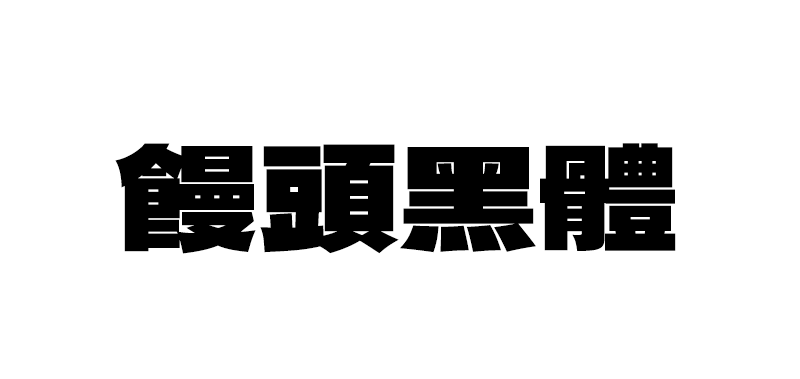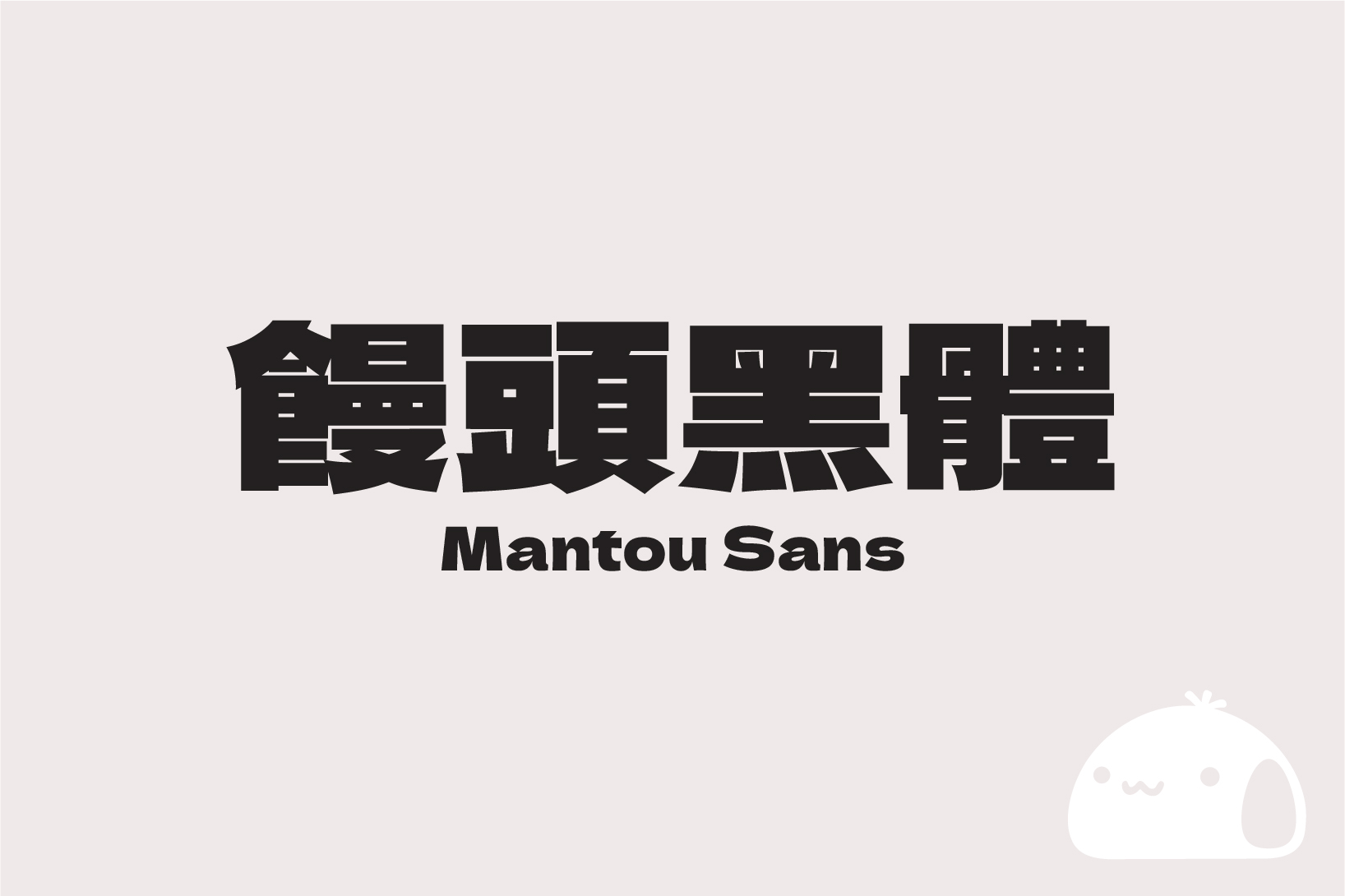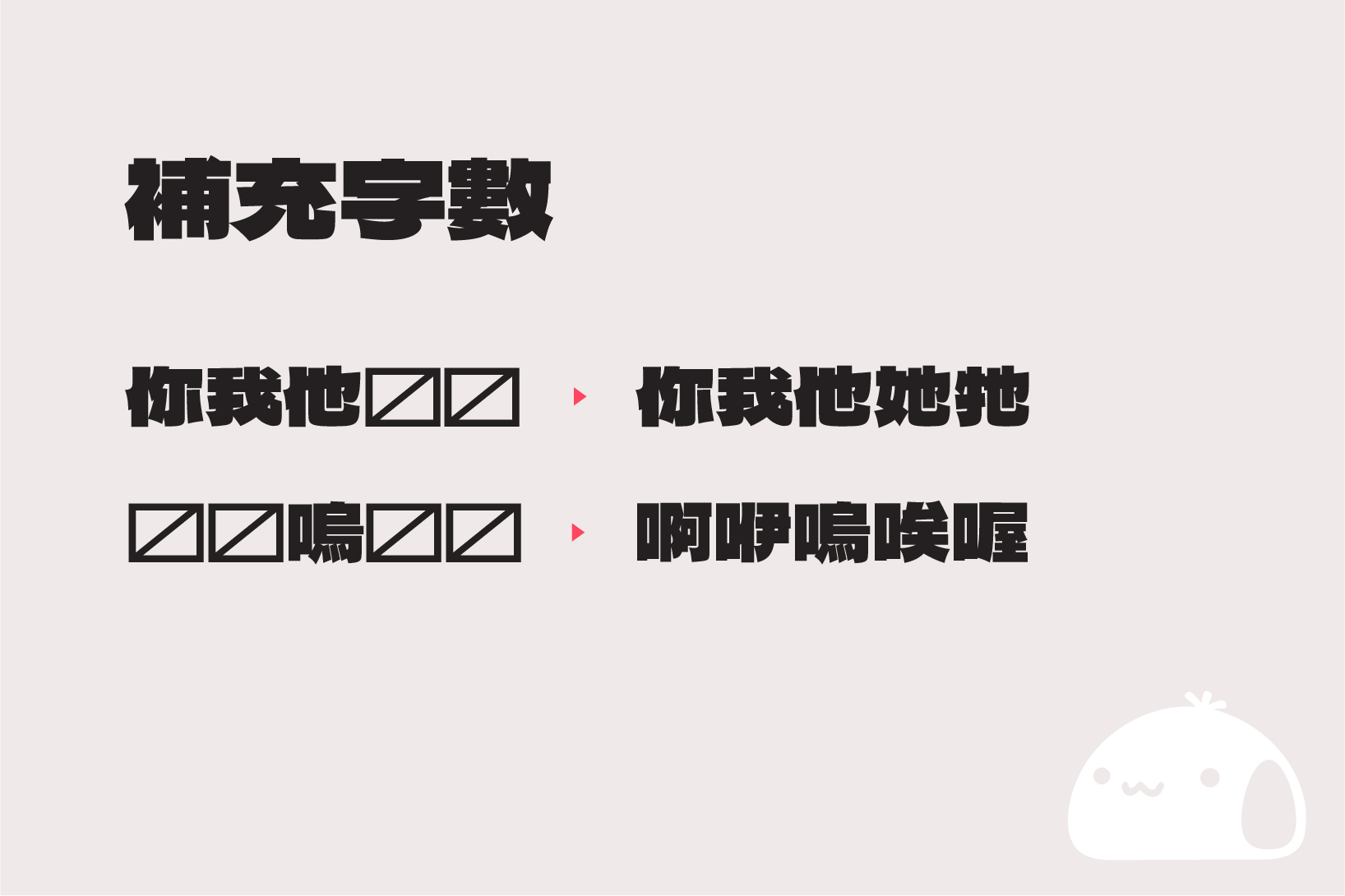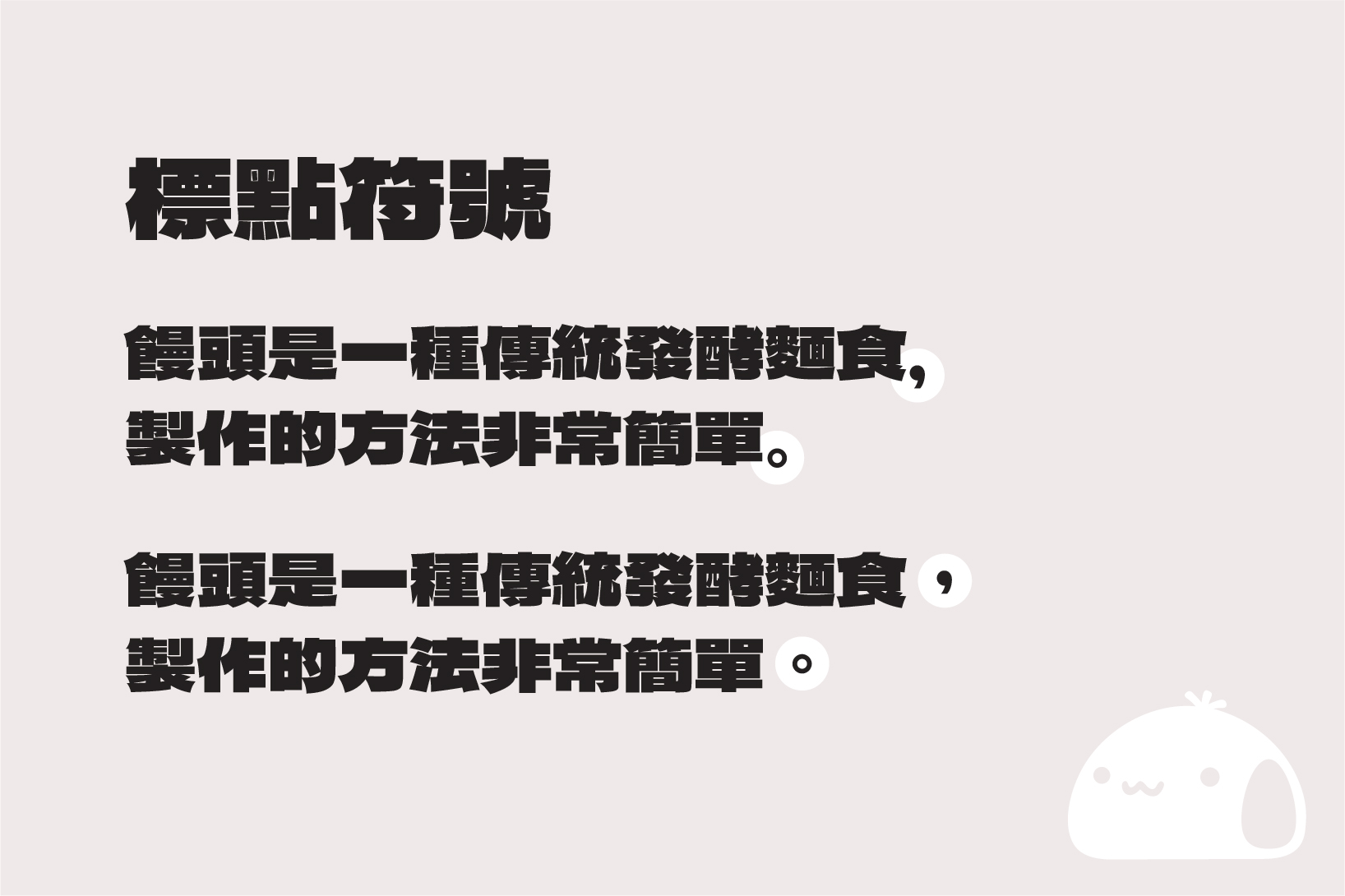
馒头黑体是基于德拉黑体(デラゴシック/ Dela Gothic One )修改而成的台湾繁体中文补充版本。
由日本设计师Artakana于2021年所开源的字体「デラゴシック(Dela Gothic One /德拉黑体)」,这是一款重量感十足的无衬线字体。其扁平且厚重的哥德式设计,不仅带给人一种坚固稳定的感觉,更有强烈的视觉效果,特别适合用于标题、海报、影片字幕或包装设计之中。
虽然这个字体已支持至「汉字jis第三水准」,但对繁体中文使用者来说,仍可能会遇到「缺字」的问题。由于我也是这套字体的爱用者,因此决定自己补齐常用的缺失字元。
本项目字体使用FontCreator 14软件进行修改,首次发布项目先根据字体表常用国字标准字体表(4808字),将缺少的字元根据字体现有的汉字进行拆解并且修改(新增共508字)。其中,全型标点符号的部分,也针对台湾使用习惯,调整符号的位置与宽度。
字体风格